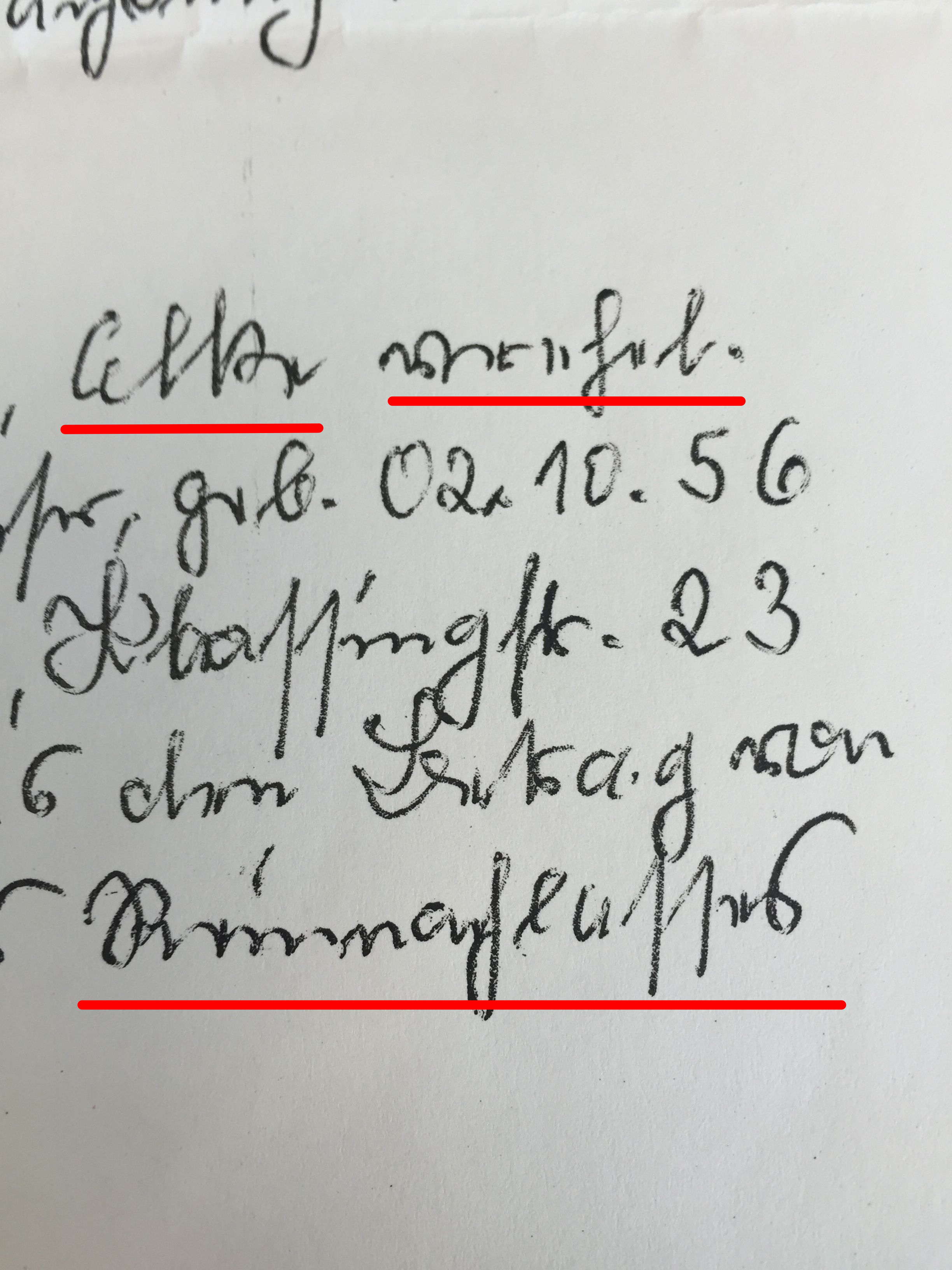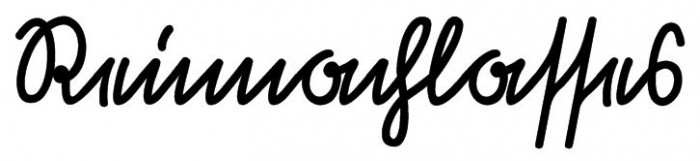
kann das jemand entziffern?
Der Suchende sagt: Kann mir bitte jemand sagen, wie die drei markierten Wörter heißen? Ich vermute, dass das dritte Wort »Reinnachlasses« heißt. Die Worte stammen nämlich aus einem Testament. Das zweite Wort könnte ein Mädchenvorname sein. Für das zweite Wort habe ich im Moment keine Erklärung; das nächste danach folgende Wort ist der Nachname der Frau deren Rufname vor dem ersten markierten Wort steht.
Vorschläge für ein paar Buchstaben des zweiten Wortes: Letzter Buchstabe ein Punkt, vorletzter ein l, davor ein e, davor ein h, würde die Silbe hel. bilden. Das erste Wort von hinten nach vorn e, k, l, erster Buchstabe ein E? … Elke? Aber das zweite Wort sollte eigentlich der Mädchenname sein, naja. (Hab vergleichend die Briefe meines Opas herangezogen, zumindest das e kommt da auch so vor)
könnte das "verehel." (verehelicht) heißen?
Kann ich auch bestätigen, passt gut, auch wenns wirklich recht flüchtig gesxchriebn ist. möglicherweise sogar vrehrl., also das erste e verschluckt:
Ist eher unwahrscheinlich, vergleiche die vermutete 6 (letzter Buchstabe im dritten Wort) mit der deutlich und anders ausgeführten Jahreszahl in der zweiten Zeile, 02.10. 56, (davor geb., auch dort ein e) letzter Buchstabe eine 6. Der vorletzte Buchstabe des Wortes vor der vermuteten sechs ist ein e, siehe zweites Wort, was ja schon als verehel. identifiziert wurde.
In der dritten Zeile steht aber wahrscheinlich eine Adresse, Klassing(?)str. 23, vergleiche auch die letzte Silbe str. mit der letzten Silbe im dritten Wort. bertels Vermutung des »Reinnachlasses« würde schon passen, denk’ ich.